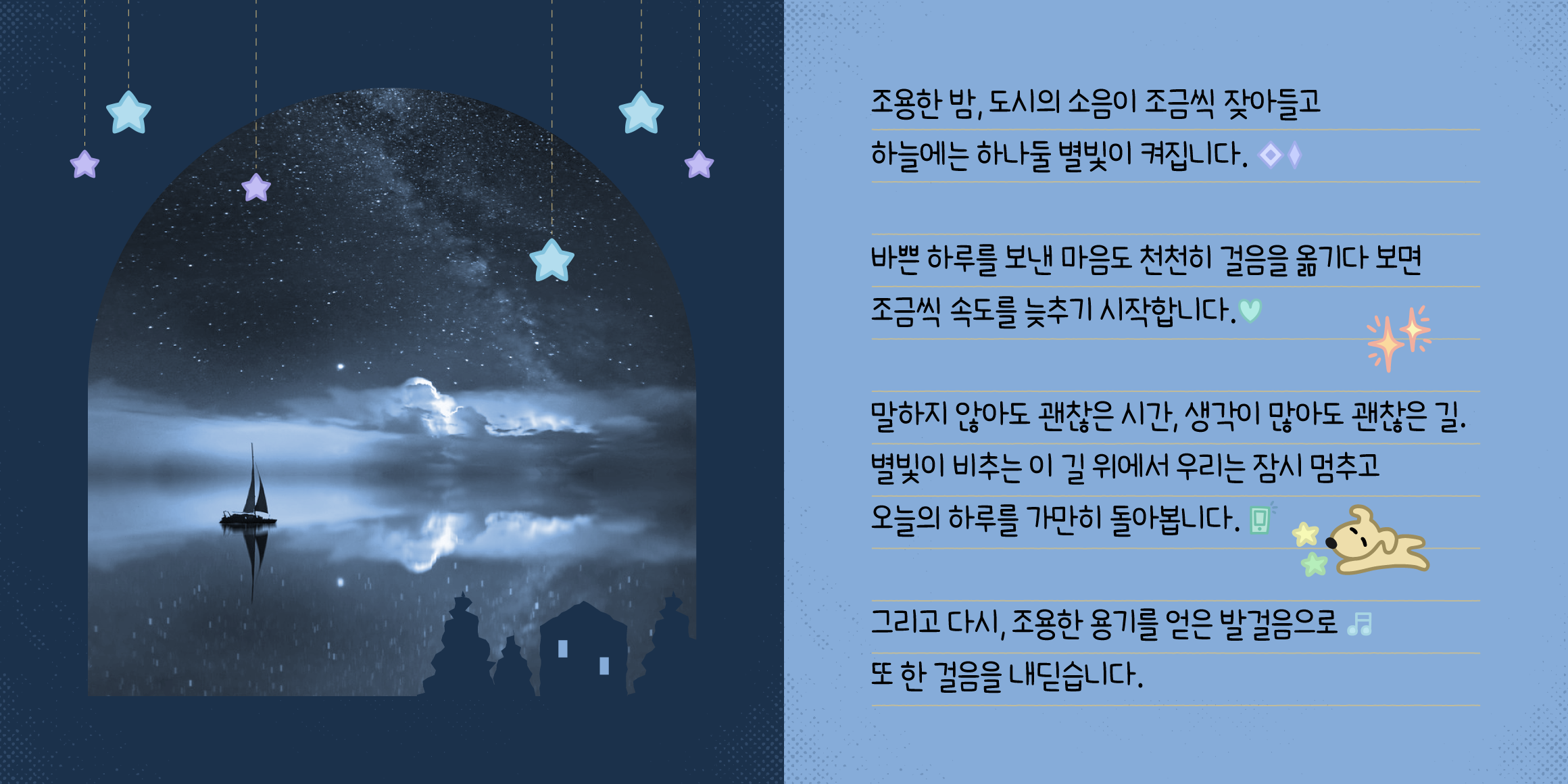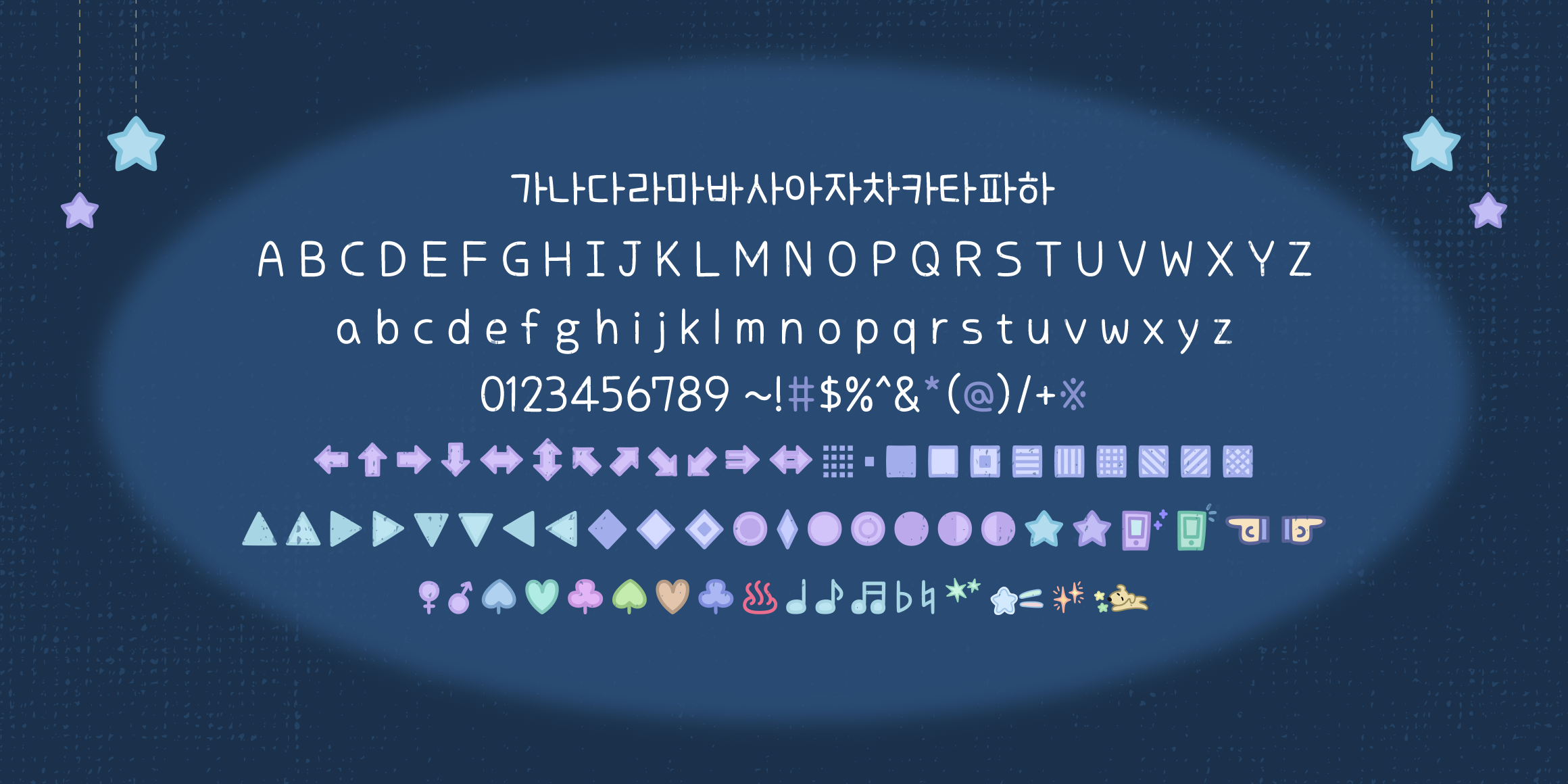
각진 글자들이 마치 뾰족한 별을 떠올리게 한답니다.
다양한 히든 딩벳을 찾아보세요!
- ;), ;>, :!:, :?: 을 치면 숨겨진 딩벳이 나와요!
-#*@※←↑→↓↔↕↖↗↘↙⇒⇔▒■□▣▤▥▦▧▨▩▲△▶▷▼▽◀◁◆◇◈◉◊○◎●◐◑★☆☎☏☜☞♀♂♠♡♣♤♥♧♨♩♪♬♭♮ 에서 컬러 딩벳을 지원합니다.
- 컬러 딩벳을 지원하지 않는 환경에서는 흑백으로 보여집니다.
하지만 마냥 각져 있기만 한 것은 아니에요. 부드럽게 각을 이룬 글자들이 모여 단정하면서도 다정한 느낌을 줍니다.
- J별빛산책 / JStarlightwalk